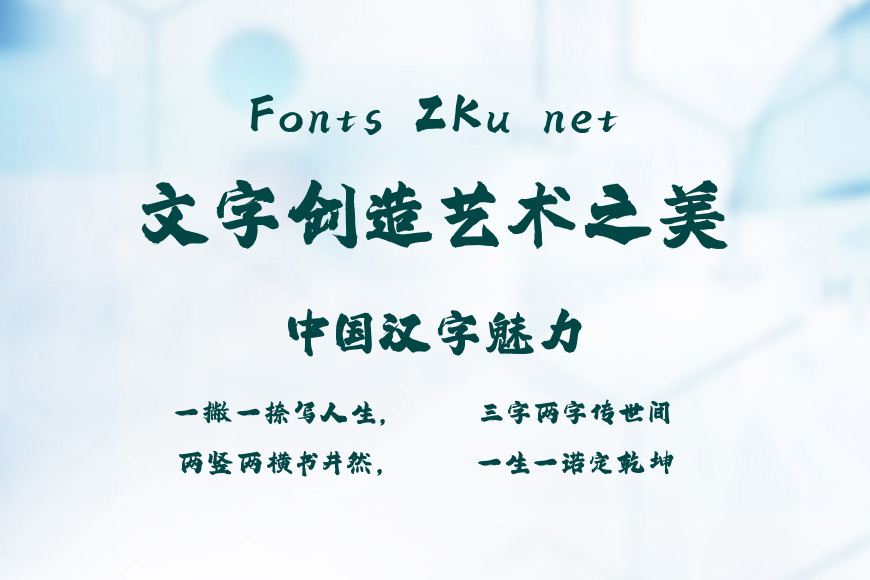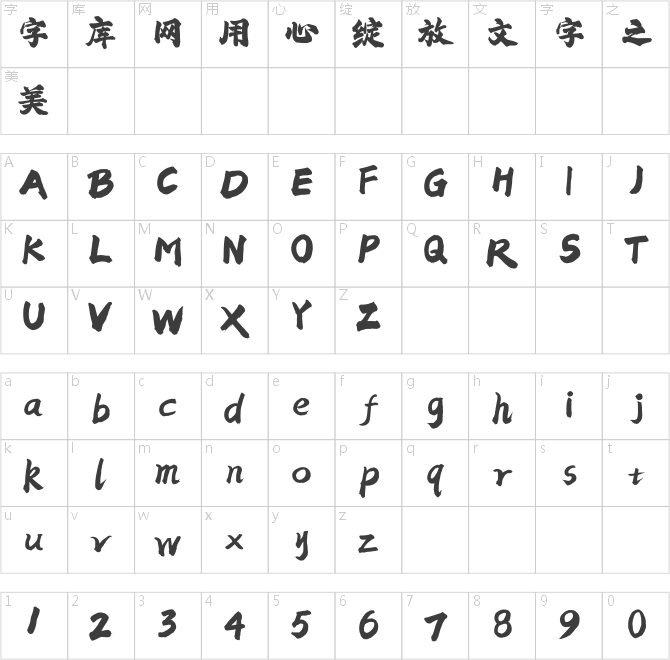
飞波正点体
字库创作历时一年时间,完成共7千多字,满足当今商业化应用的需求。字体风格稳重, 气势上扬,笔画厚重有力是此套字库的特点。适用于各种标题大字排版,电影海报、包装、 电商、品牌名称、漫画、影视综艺、游戏、各类商业海报、户外广告标题等。
飞波正点体字体字库是一款让人赏心悦目、百看不厌的中文字体,适合各类广告和产品包装设计应用,字体大小15.24MB,格式为otf字体,上传用户是晓语无声,作者/版权方为黄飞波